フォントワークス「LETS」より、新機能「フォントリスト共有機能」提供開始。無料会員登録で特典フォントも多数使える
フォントワークスは、年間定額制フォントサービス「LETS」の新機能として「フォントリスト共有機能」を追加したことを2022年2月17日に発表した。
「フォントリスト共有機能」により、サービス利用者間でのフォントリストの共有が可能となり、社内外でプロジェクトに応じたフォント環境を実現できる。
LETSとは
2002年からフォントワークス株式会社が提供している、業界初の年間定額制フォントサービス「LETS(Leading Edge Type Solution)」。
高品位でバラエティ豊かなフォントがすべて使用できるフォントサービスです。多彩なラインナップで、日本語、欧文、韓国語、簡体字、繁体字、タイ、ヘブライなどの各種フォントを提供している。
2021年2月には「クリエイティブ活動をより加速する」サービスとして新しく生まれ変わり、この度1周年を迎えた。
フォントリスト共有機能について
LETSサイト内で共有リンクURLを発行し、そのURLをメール等で共有することで、サービスご利用者間でのフォントリストの共有が可能。
共有されたURLを押下すると、フォントリストが自動的にインポートされる。
フォントリストの内容は変更可能。
フォントワークスのおすすめフォントリスト
新機能「フォントリスト共有機能」提供開始に伴い、フォントワークスがおすすめするフォントを、カテゴリごとでリスト公開した。
なおこちらのフォントリストは、今後も随時追加していくようだ。
書体デザイナー・藤田重信氏による、厳選書体に対してのコメント
フォントワークスのおすすめフォントリストの一つとして、「書体デザイナー厳選書体~藤田重信~」を公開しました。本リストに収録された各書体に対する、フォントワークス書体デザイナー・藤田重信氏のコメント。
『究極の優雅な明朝体です』:筑紫Aヴィンテージ明L
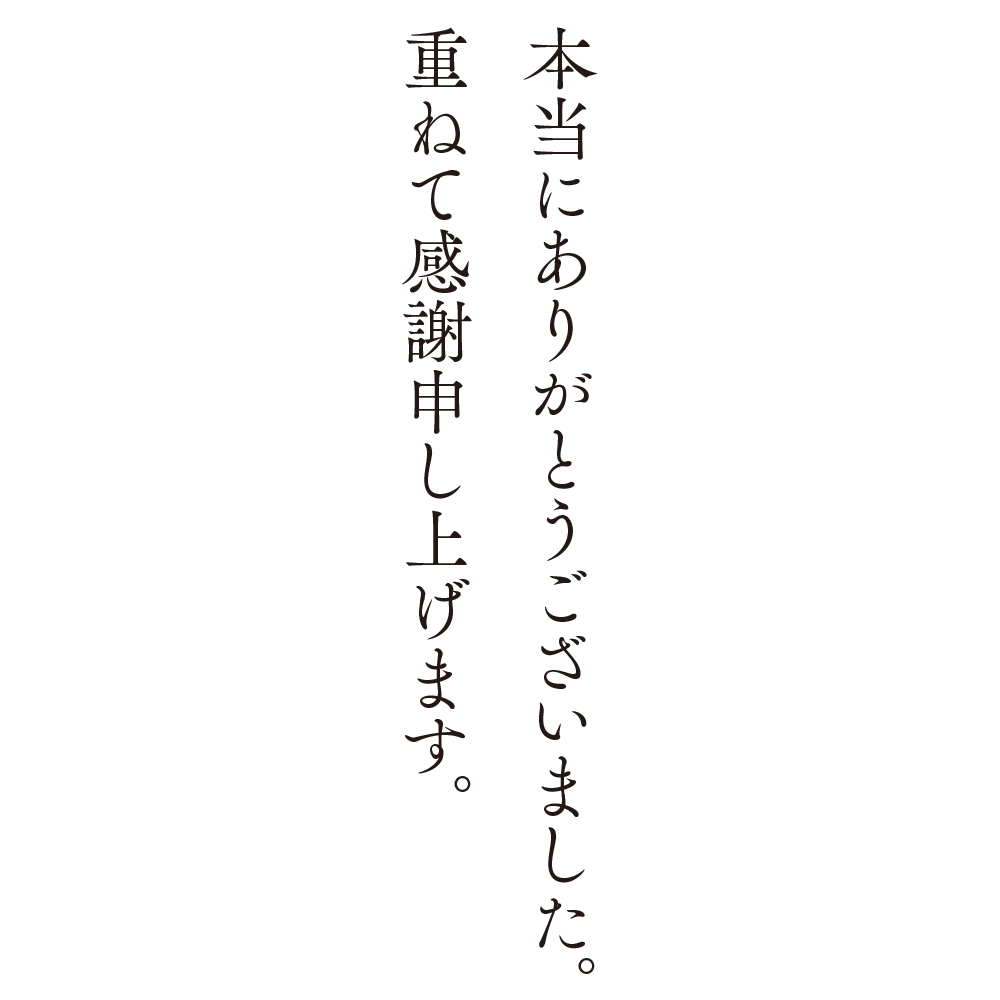
「筑紫シリーズ」の明朝体の中でも最上位の、高貴で優雅な品位を見せる書体です。大人の上品かつ丁寧な言葉のテキスト組用にと、開発・設計・デザインしました。
『とにかく躍動感!の明朝体です。』:筑紫Bヴィンテージ明L
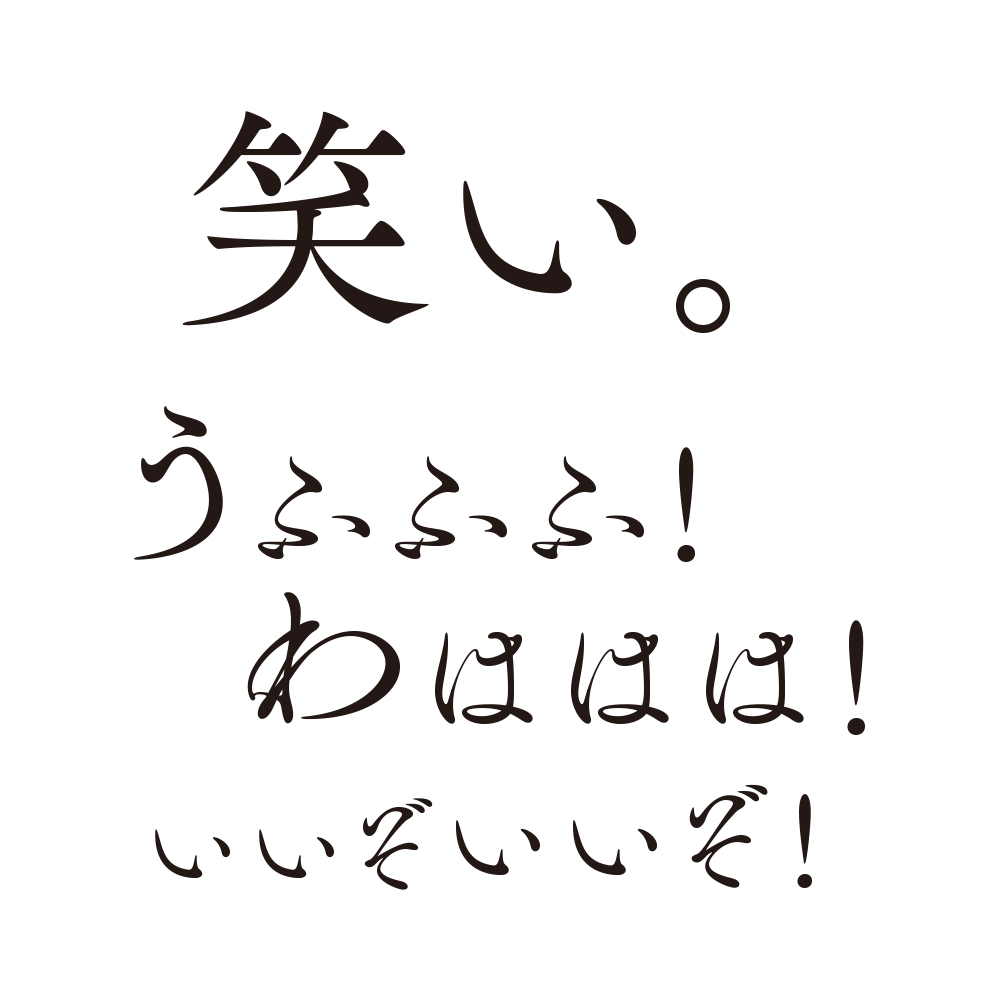
「プロフェッショナル仕事の流儀」撮影中に、祖父江慎氏がふと見せてくれた、福沢諭吉編の「手習の文」。
その中の「ふ」に感動し、それに合わせた50 音全仮名デザインさせたもの。
『男性的な力強い明朝体です。』:筑紫Cヴィンテージ明L
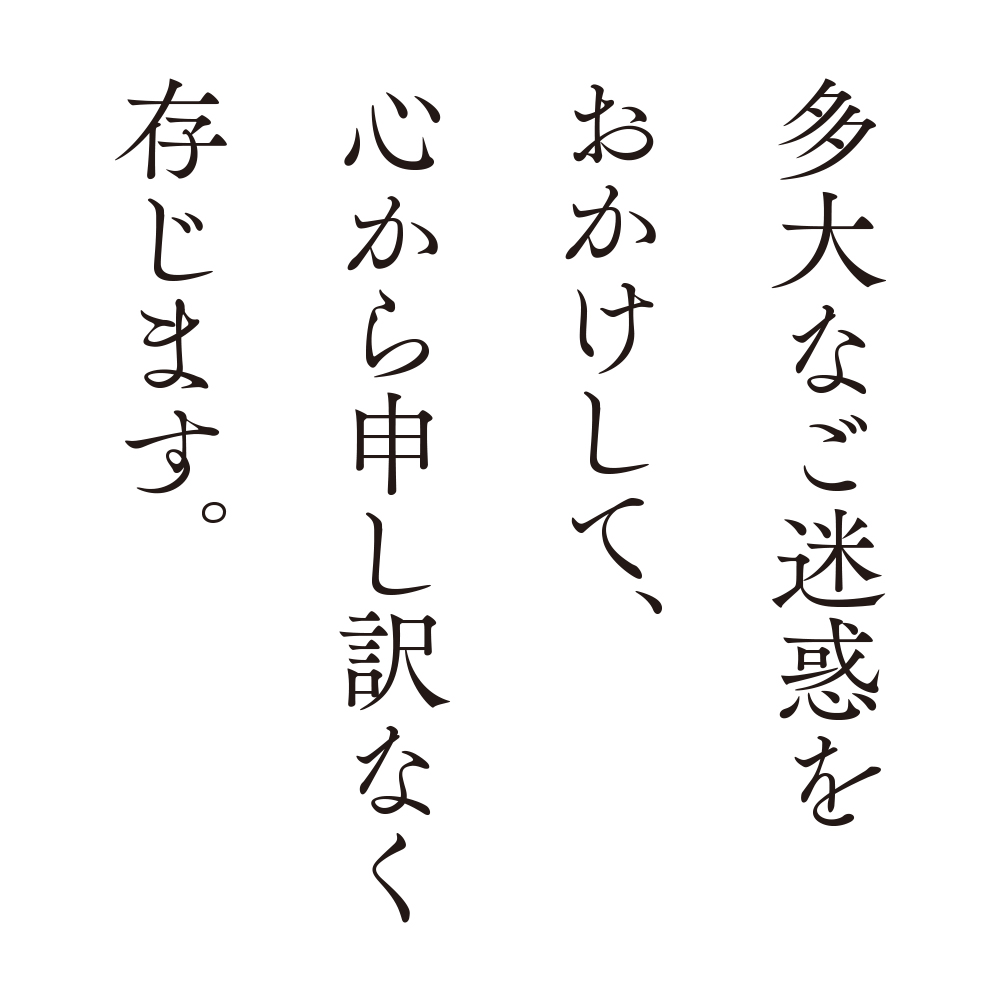
「筑紫シリーズ」の明朝体の中でも最上位の、端正かつ力強い品位を見せる書体です。大人の剛毅で繊細な言葉のテキスト組用にと、開発・設計・デザインしました。